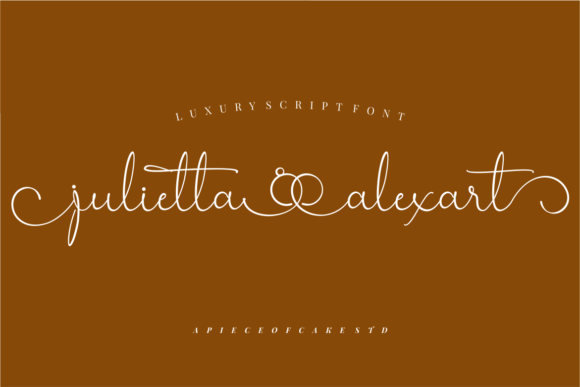
Julietta Alexart - это манящий шрифт, созданный для создания элегантной атмосферы.
Ищите ли вы шрифты для Instagram или каллиграфические шрифты для проектов DIY, этот шрифт превратит любую творческую идею в настоящее произведение искусства!